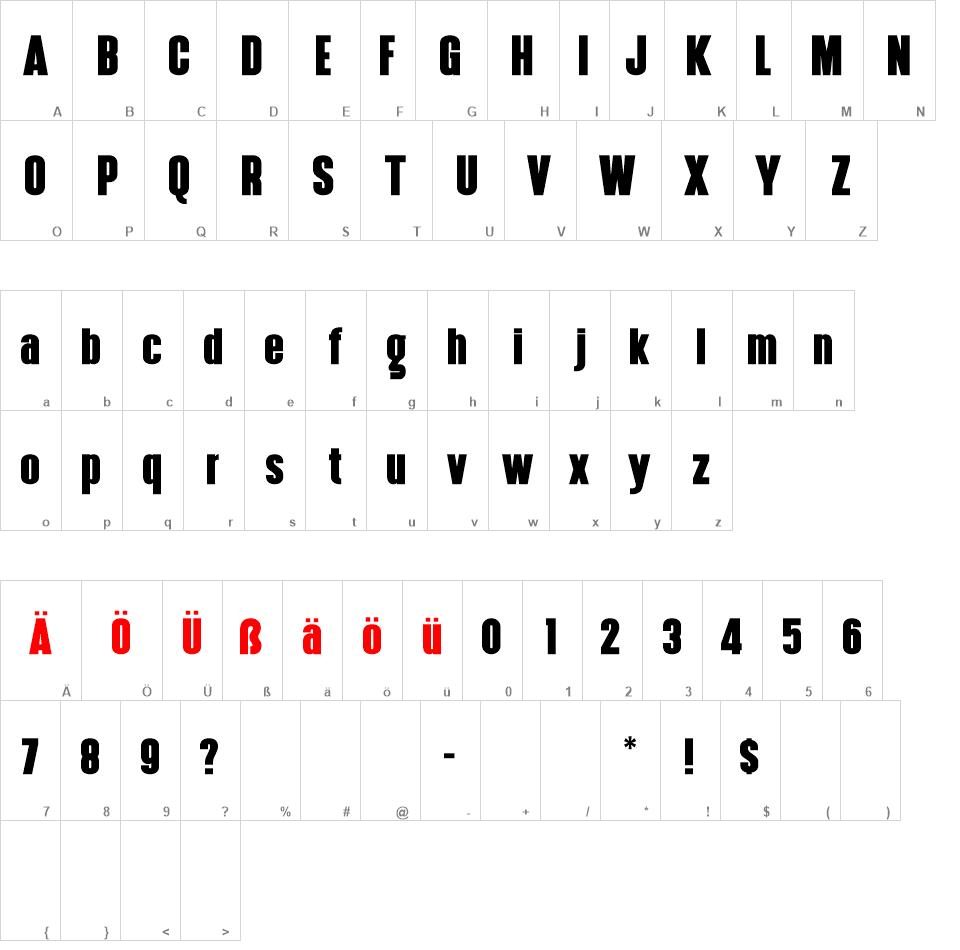
Hennigar
Hennigar font
Hennigar ist eine Neo-Grotesk-Sans, die für die Anzeige von Text und Überschriften entwickelt wurde. Ähnlich wie Impact und Amsterdam auf den ersten Blick, basieren viele der abgerundeten Buchstaben auf dem Aussehen des Buchstabens O mit sehr geringen Breitenunterschieden. Aufgrund ihrer kondensierten Beschaffenheit sind die Öffnungen eng mit Extendern, die weit unter die Basislinie fallen. In ähnlicher Weise basieren viele der Kleinbuchstaben auf dem Kleinbuchstaben o. Terminals und Tails zeigen immer nach Osten / Westen, wodurch das gesamte Alphabet sehr einheitlich wirkt. Latein, erweitertes Latein, Diakritik, Interpunktion, mathematische Symbole, Wissenschaft